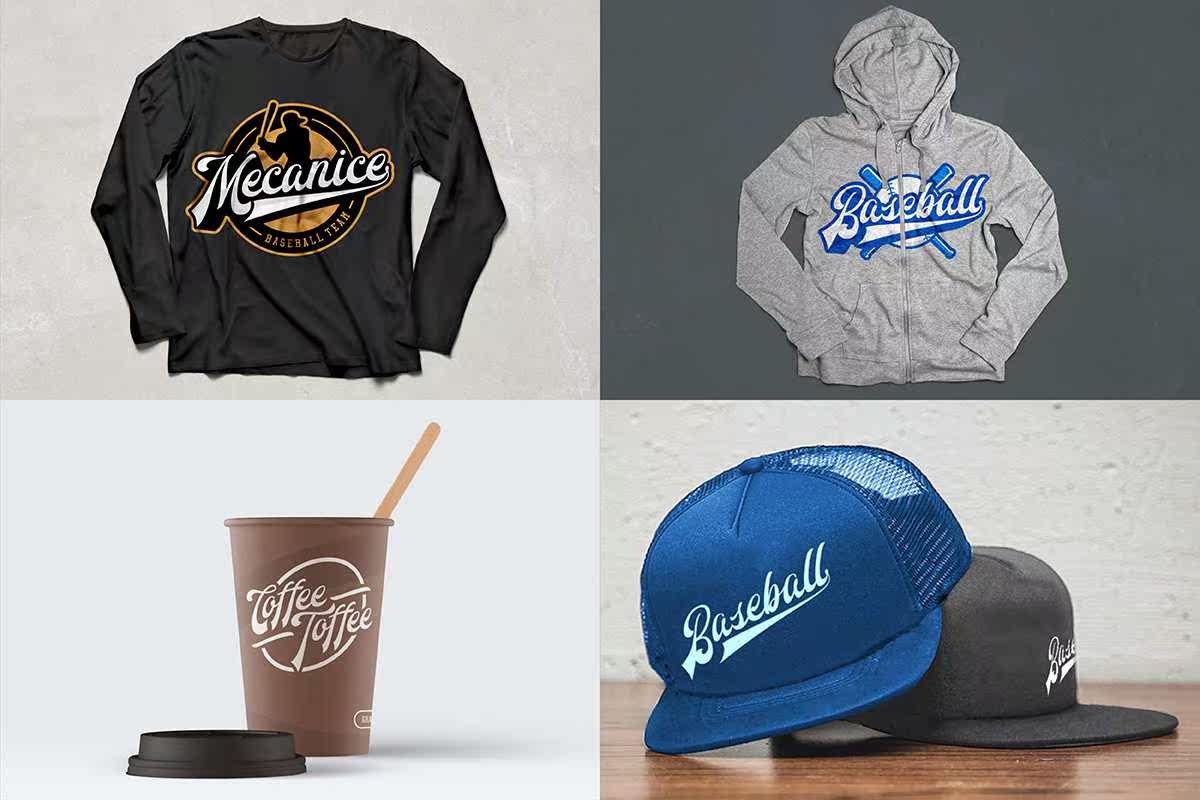
RedouraFontDu为70年代的字体和ScriptSportsFontStyle所启发的字体,这两种字体完全适用于徽标/文字标记,尤其适用于PortsMelogos。ScriptFontDu采用了一系列完美的配对字体。RedouraScriptFont包括大小写字符、标点符号、数字、,和多语言支持。它还提供了许多OpenTypeAlternates和Ligatures。根据70年代的字体样式和ScriptSportFontStyle的启发,RedouraFontDuoIsascripttTypeFaceFace可用于徽标/文字标记,特别是对于PortsMelogos。ScriptFontComes具有丰富的打印字体。RedouraScriptFontStyle包括大小写字符、标点符号、数字、,和Multilanguage Support.Italsohasmany OpenTypeAlternates和Ligatures。